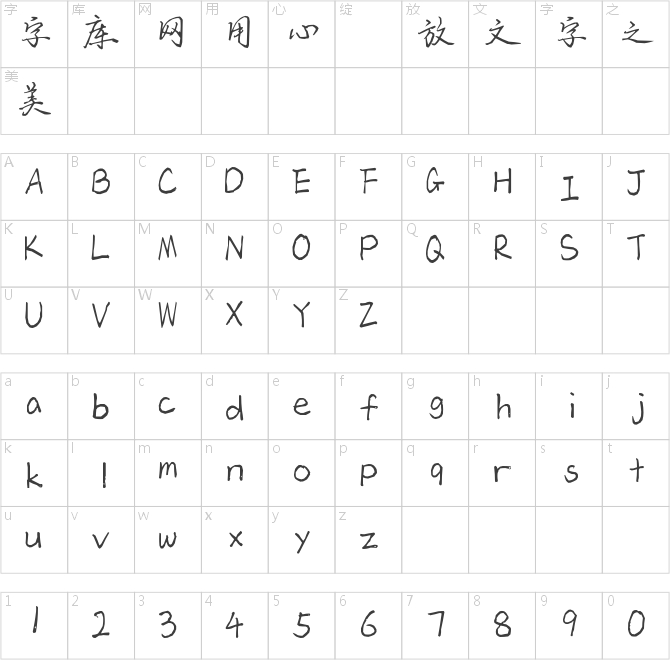
安康胡乱瞎写手写硬笔
安康胡乱瞎写手写硬笔字体下载安康胡乱瞎写手写硬笔字体两千五常用字系列一点零版本
安康胡乱瞎写手写硬笔字体两千五常用字系列一点零版本字库是一款让人赏心悦目、百看不厌的中文字体,适合各类广告和产品包装设计应用,字体大小1.13MB,格式为ttf字体,上传用户是17199970014,作者/版权方为未知